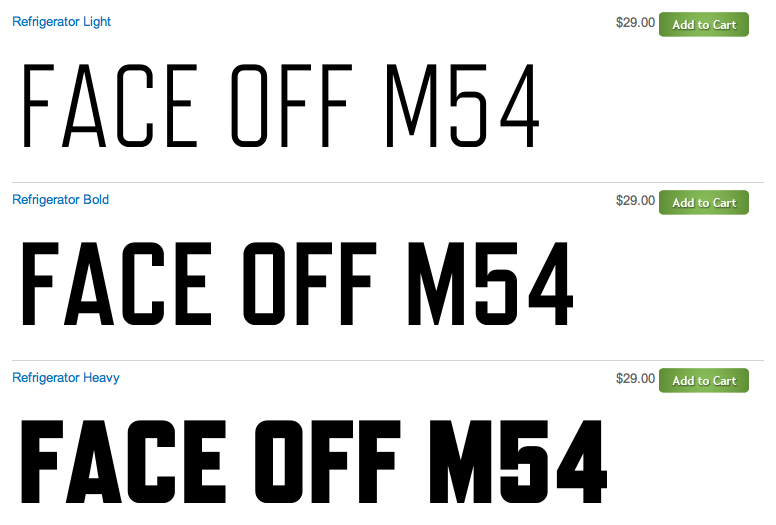
Suche dringend ähnliche Schrift wie "Face Off M54"
Hallo- ich suche ganz dringend eine ähnliche Schrift wie die "Face off M54". Allerdings benötige ich mehrere Schriftschnitte und vor allem fetter. Ansonsten sollte die Typo International einsetzbar sein inkl. Umlaute etc. Die Schrift ähnelt der College Typo, aber hat mehr Rundungen!
Auf der Seite von Fonthaus (habe noch nie von der Firma gehört, ich hoffe, sie ist lizenztechnisch integer) gibt es diese hier: